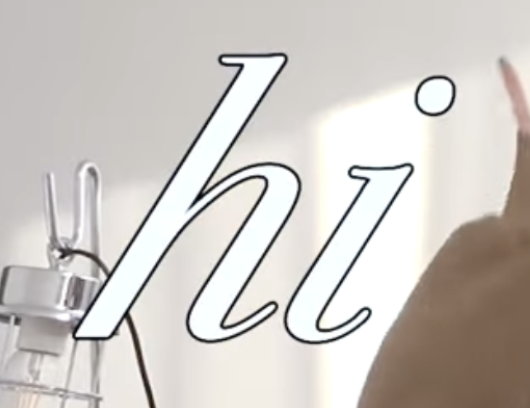
이 폰트 뭔지 궁금해요
FF Danubia Std Bold Italic 기울인거같아요 https://www.myfonts.com/products/ot-bold-italic-danubia-366963?queryId=2a7a5c0b0dbafba917339bd70dc793a8&index=universal_search_data&objectIDs=5830083000